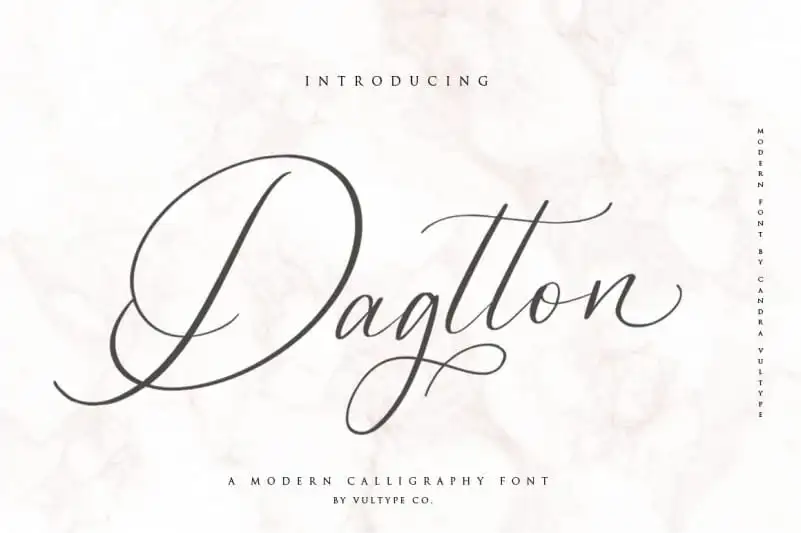
A Dagtton Calligraphy Font é uma escolha ideal para quem busca uma mistura sutil de beleza minimalista em cada caractere. Ela foi criada pelo designer Vultype e compartilhada através do site 99designs, um dos principais lugares online onde designers anunciam suas criações. Este script calligrafiado é conhecido por sua natureza fluida e artesanal, com uma delicadeza que enriquece cada letra. Convidamos você a mergulhar neste estilo único e eterno da Dagtton Calligraphy Font, um verdadeiro toque de elegância para os projetos mais pessoais. Se apaixone por seu estilo distintivo e singular, pois ele é perfeito para transformar seus trabalhos em designs de alto nível e impacto visual.